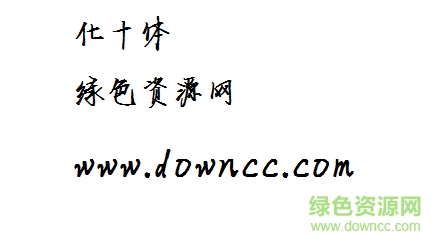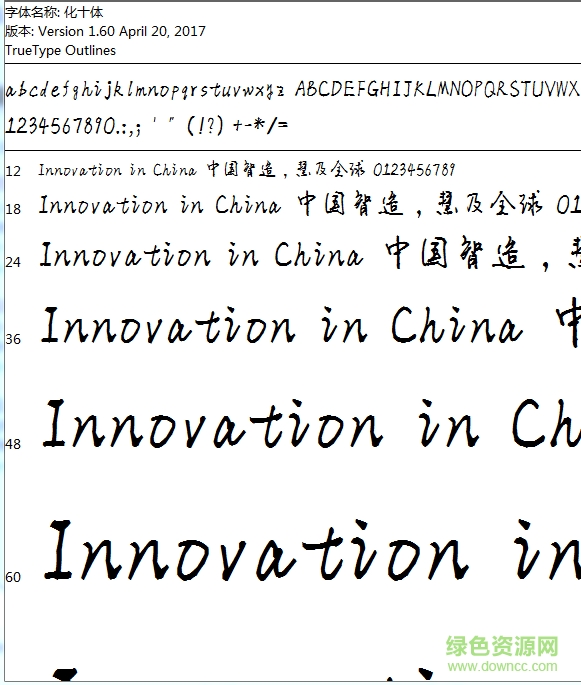
化十體是一款好看的中英文字體,字體藝術氣息十足,筆畫形如流水,整體效果非常優(yōu)美,喜歡這款字體的朋友歡迎到綠色資源網(wǎng)下載使用!
化十體字體是一款應用于藝術設計方面的英文字體,該字體筆畫正規(guī),可以廣泛應用于名片設計、新聞媒體、宣傳海報、ppt、影視制作以及內(nèi)容用字等領域。